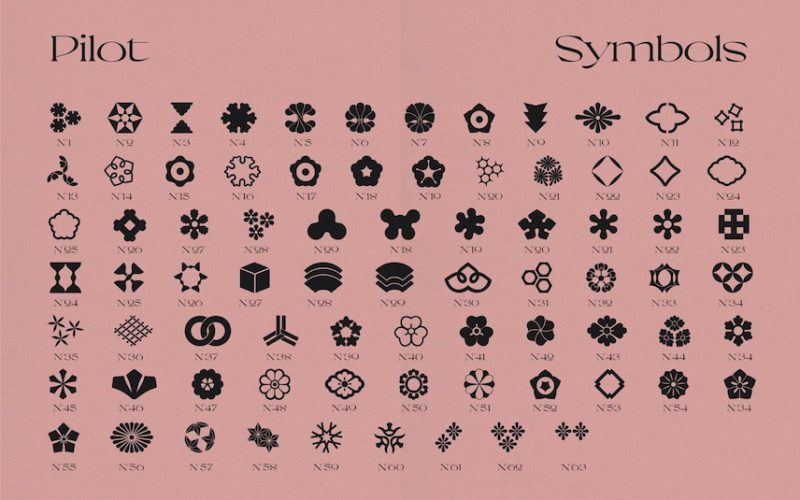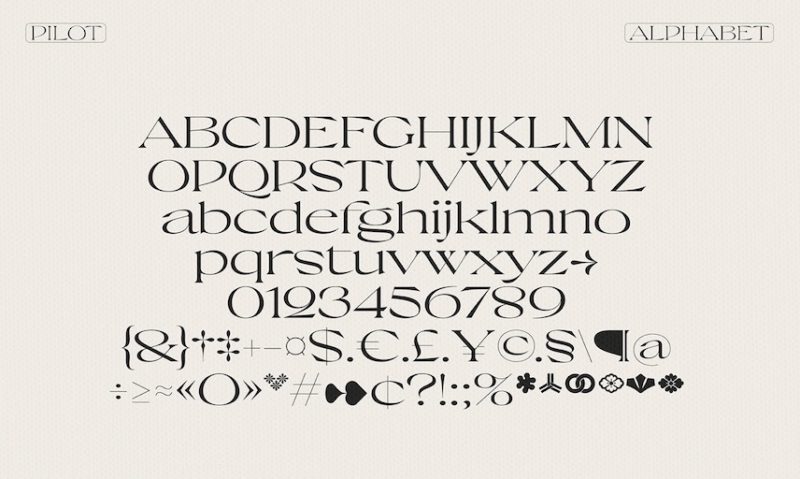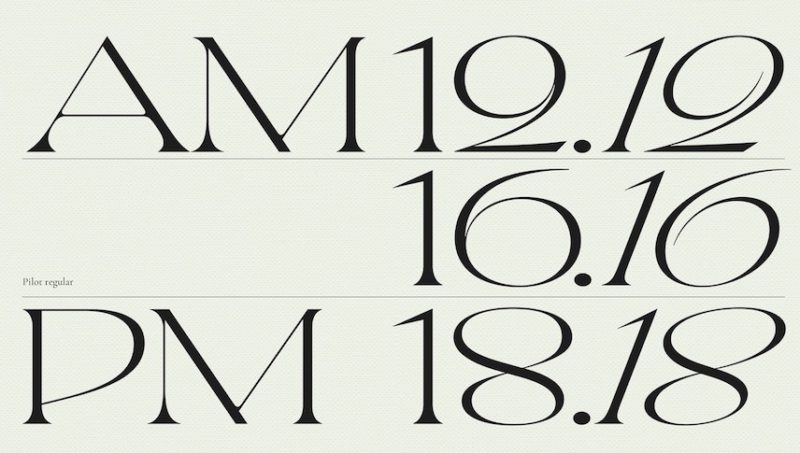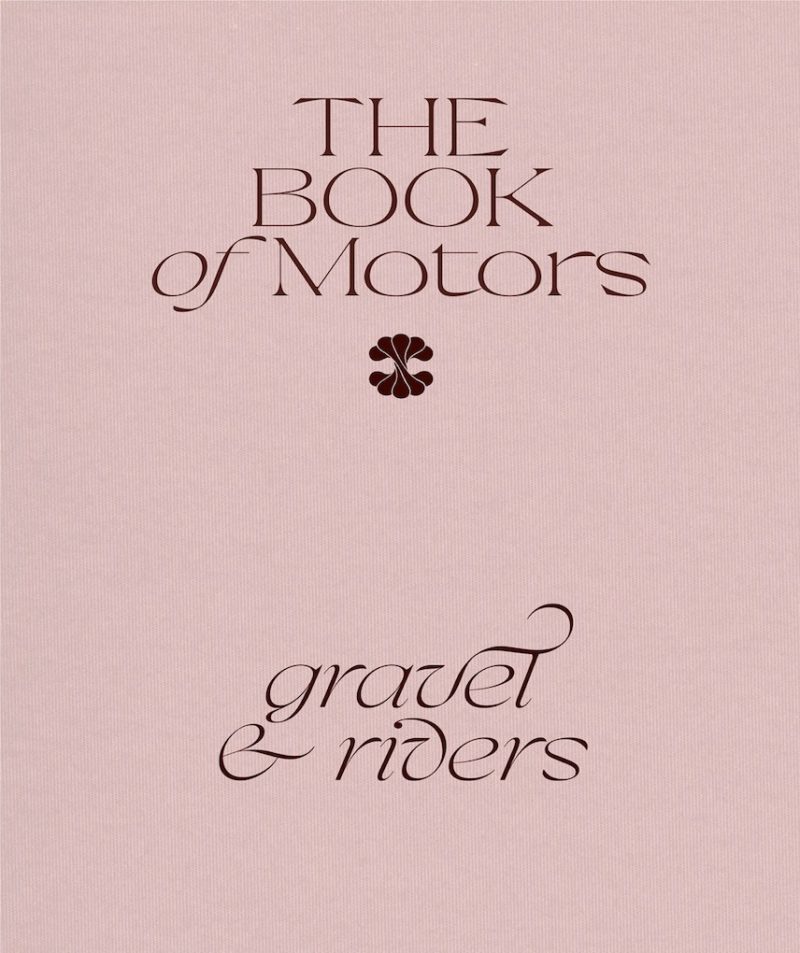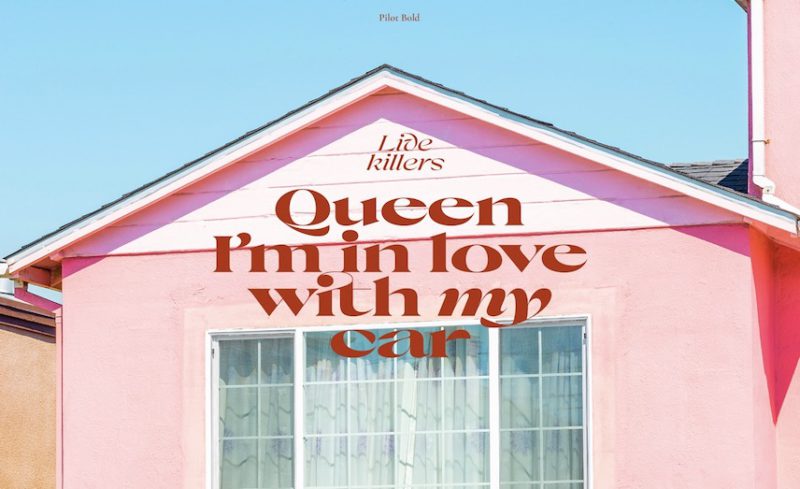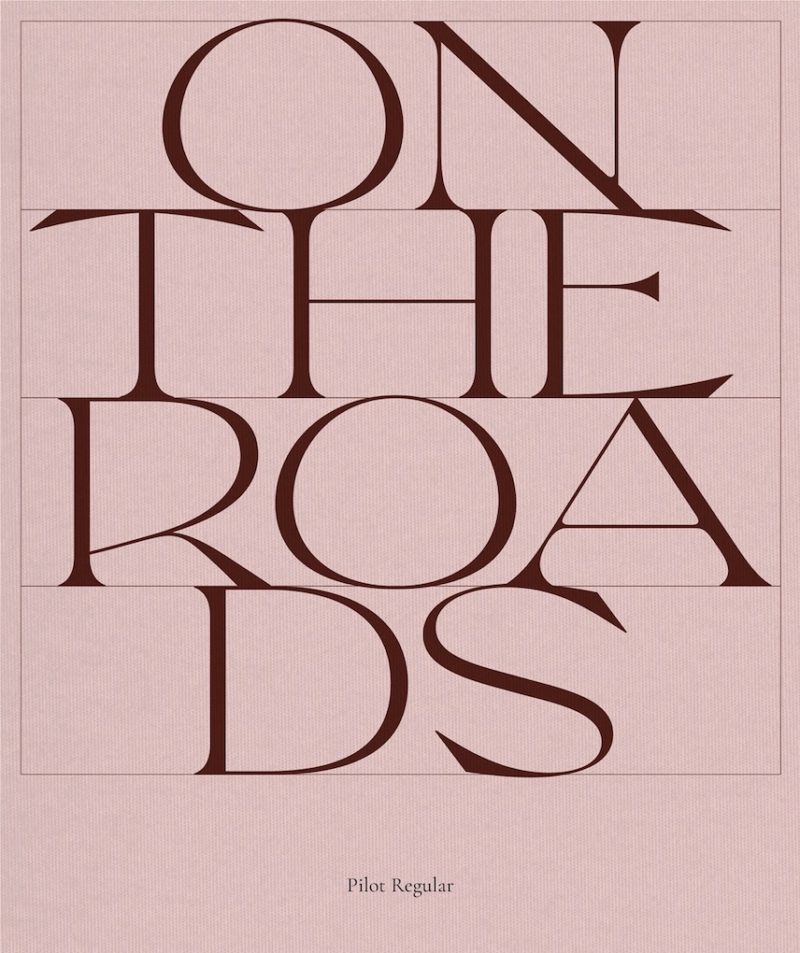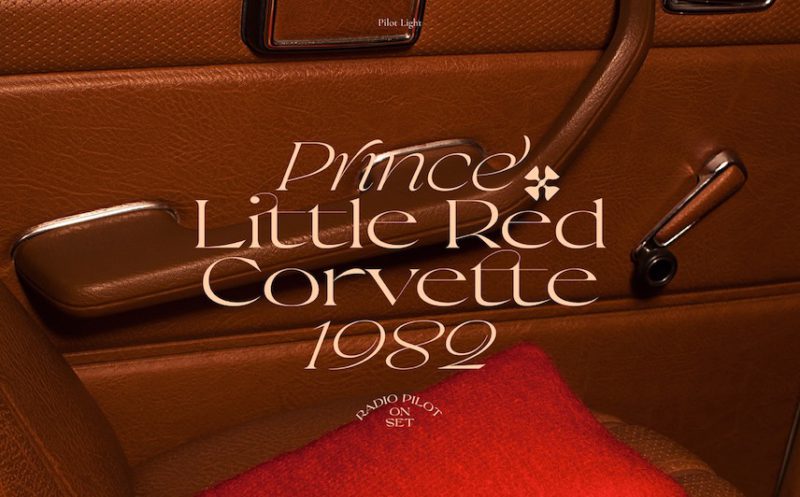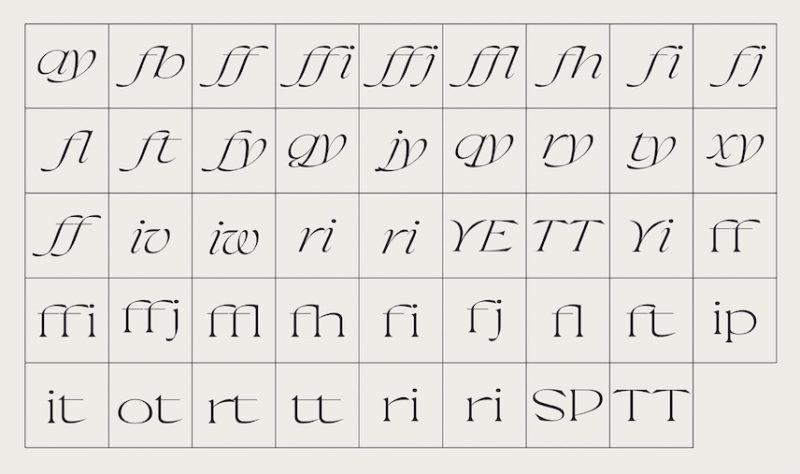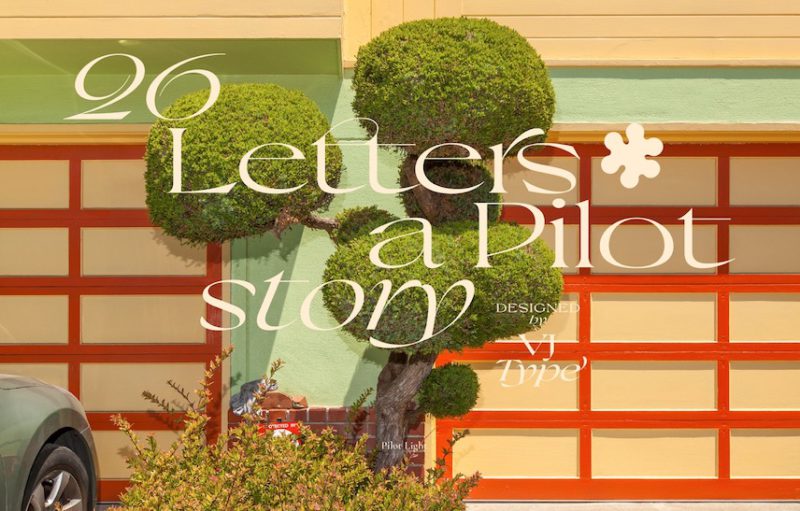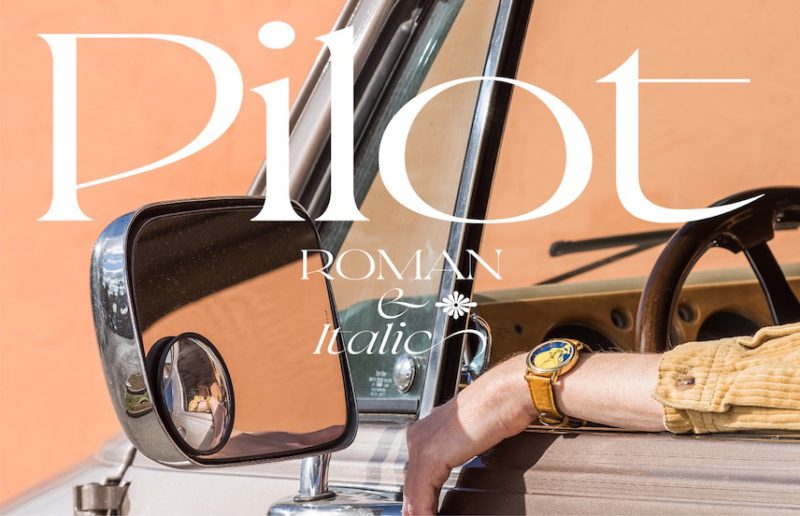
Para resistir el paso del tiempo
Buenas noticas para la tipografía, esta vez son de Francia y cómo no, llegan de la mano de Violaine & Jeremy, el estudio multidisciplinar parisino dirigido por Jérémy Schneider y Violaine Orsoni. Se trata de Pilot, una deliciosa familia pensada, según cometan sus propios creadores, para los devotos entusiastas de la moda. «Esta fuente nació del deseo de crear una tipografía extendida contemporánea de elegancia innegable. Nos la imaginamos perfectamente integrada en editoriales de moda y sesiones fotográficas. Pilot fue diseñada para resistir el paso del tiempo. Al igual que las prendas clásicas de un guardarropa, cada detalle ha sido cuidadosamente diseñado para lograr un alto sentido de equilibrio, combinando acentos femeninos y masculinos por igual.
Pilot es una tipografía serif display, disponible en 10 estilos, desde light hasta black, tanto en romano como en cursiva. Destaca por su generosidad, tanto en la esencia de su diseño como en la amplitud de su conjunto de glifos y características específicas. Combina terminaciones angulares y puntiagudas con curvas suaves y transiciones fluidas en las diagonales. El conjunto de glifos ha sido enriquecido con una amplia gama de ligaduras, alternativas y florituras expresivas, además de un conjunto de 77 símbolos y 18 flechas estilizadas.
«El estilo romano representa el lado majestuoso de Pilot: maduro, elegante y visionario. La cursiva, por otro lado, es más experimental, incluso audazmente expresiva. De hecho, esta es nuestra primera incursión profunda en el diseño de cursivas, y no nos hemos puesto límites».